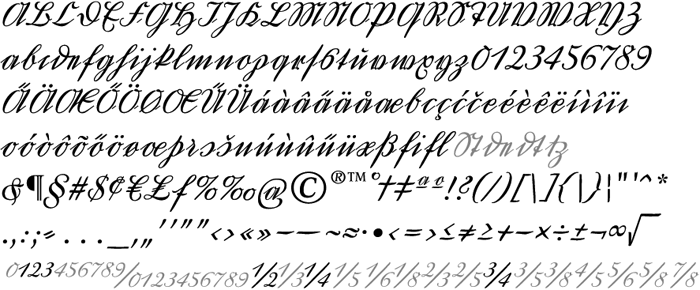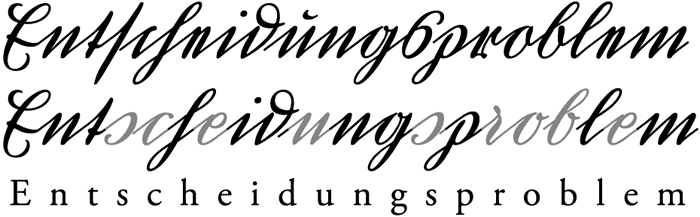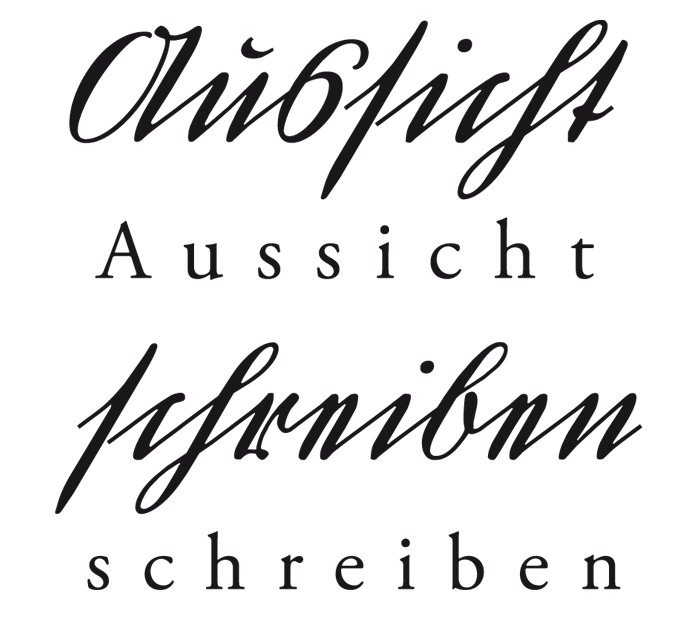
Um einen handschriftlichen Text von Goethe oder Schiller (siehe oben) zu lesen bedarf es einiger Übung. Sie schrieben – wie ihre Zeitgenossen auch – zumeist in Kurrentschrift. Manch einer mag diese Schrift noch von den Großeltern kennen. Die Kurrentschrift war vom Ende des Mittelalters bis in die Mitte des 20. Jahrhunderts eine gängige Schreibschrift in deutschsprachigen Ländern. Man kann sie die geschriebene Tochter der Fraktur nennen.
Im Gegensatz zu Ländern wie Italien oder Holland, wo die Humanisten der Renaissance die lateinische Schrift populär machten, konnte diese im deutschsprachigen Raum die Kurrent lange Zeit nicht verdrängen. Zwar wurden lateinische Texte oft mit lateinischen Buchstaben verfasst, aber im Alltag wurde meist »gotisch« geschrieben. Ausgehend von der gotischen Kursive des Mittelalters haben Schreibmeister ab etwa 1450 die Formen der deutschen Kurrentschrift entwickelt. Indem sie die einzelnen Buchstaben durch lange Anstriche miteinander verbanden, wurde sie zügiger und leichter zu schreiben. Gleichzeitig konnten die Schreiber es jedoch nicht unterlassen, mit dekorativen Übertreibungen ihre Fähigkeiten zur Schau zu stellen. Mehrere Schriftreformen steuerten dagegen. Die letzte dieser Reformen fand Anfang des 20. Jahrhunderts statt, als Ludwig Sütterlin seine Version einer Laufschrift entwickelte, die fortan einfach Sütterlin genannt wurde. Sie wurde aufrecht geschrieben, war breiter, und verzichtet auf den Strichstärkenkontrast von feinen und fetten Strichen. Die Sütterlin wurde schließlich die Standardsschrift in deutschen Schulen – bis zum Normschrifterlass.
Vergleich von Kurrent und lateinischer Schreibschrift aus einem österreichischen Schriftvorlagen-Heft
Merkmale
Heute ist die Kurrentschrift für viele nahezu unlesbar, denn ihre Buchstaben unterscheiden sich zum Teil stark von der lateinischen Schreibschrift. Auffallend sind die geraden Striche und sehr spitze Winkel in vielen Kleinbuchstaben, die der Schrift auch den Namen »Spitzschrift« einbrachten (Im Gegensatz zur »runden« lateinischen Schrift).
Alphabet der Deutschkurrent von Georg Salden
Die Kleinbuchstaben a, b, f, g, i, l, m, n, o, q und t sehen kaum anders aus als die lateinischen. Das gotische h hatte rechts eine Unterlänge, die im Kurrent-h verschliffen und gebunden wurde. Das e, man kann es für ein schmales n halten, hat sich in Stufen aus dem e der humanistischen Kursiven entwickelt. Es wurde nämlich nicht nach heutiger Schreibweise in einem, sondern in zwei Zügen geschrieben.
Die Kurrent vermeidet die sogenannten Deckstriche unserer heutigen Schulschriften. Das ist das Hin- und Zurückschreiben auf derselben Spur. Sie macht daraus nebeneinander geschriebene, gerade Striche (siehe r), oder bei den Großbuchstaben Kurven nach oben (siehe R). Diese Großbuchstaben sind zum Teil vergrößerte Kleinbuchstaben (A, D, G, O, Q, S, T, U, V, W, Y und Z) oder folgen den Lateinformen (B, E, F, H, I, J, L, P, R). Nur M und N, V und W gehen auf unziale Vorbilder zurück, wobei die Formen der V und W auch für die Kleinbuchstaben Modell standen. D und d scheinen unzial/griechische Vorbilder zu haben.
Das u ist mit einem darüber liegenden Haken ausgestattet, um es vom n zu unterscheiden. Wie in den gedruckten gebrochenen Schriften, kamen auch bei der Kurrent zwei s-Formen (Å¿/s) zum Einsatz. Die Umlaute ä, ö, ü wurden anfangs ae, oe, ue, später mit einem kleinen, darüberliegenden e geschrieben. Dieses e wurde dann zu zwei Strichen vereinfacht – der Ursprung unserer Umlaute.
Die Deutschkurrent
Schriftgestalter Georg Salden hat nun eine Kurrentschrift als professionellen OpenType-Font herausgebracht. Salden begann selbst im Alter von 5 Jahren Sütterlin zu schreiben. Später studierte er an der Hochschule Originaltexte in deutscher Kurrentschrift. Als Vorlage für die digitale Schrift schrieb Salden zunächst mit Spitzfeder und Tinte. Darauf aufbauend zeichnete er eine Kurrentschrift, die besonders gut lesbar ist, weil sie alles Überflüssige und Dekorative vermeidet. Die Outline der Deutschkurrent hat zudem eine eher raue Anmutung, so dass der Eindruck von Handgeschriebenem entsteht.
Zeichenbelegung der Deutschkurrent
Neben einigen Ligaturen enthält die Schrift Deutschkurrent für die gängigsten Schriftzeichen ihre lateinischen Entsprechungen, die formal in den besonderen Charakter der Kurrent eingepasst wurden. So besteht die Möglichkeit, auch nicht-deutsche Texte zu schreiben oder einen Text auch für ungeübte Kurrentleser einigermaßen lesbar zu halten, ohne den unverwechselbaren optischen Eindruck der Schrift aufzugeben. Die alternativen Zeichen können mittels OpenType-Feature angesteuert werden.